这个三八节,成为你喜欢的那个自己!
每年的三八节,都是妇女友好日,今年感觉更加正式了。
除了放假的特权,这几年女性力量也在逐渐觉醒,比如早年前,不喜欢被叫做妇女,喜欢“女生节”、“女神节”、“女王节”这样的标签。
近几年,又很厌恶这样的标签,觉得是商家营销出来的,而妇女节则是百年来女性争取平等的节日,这才是正名。
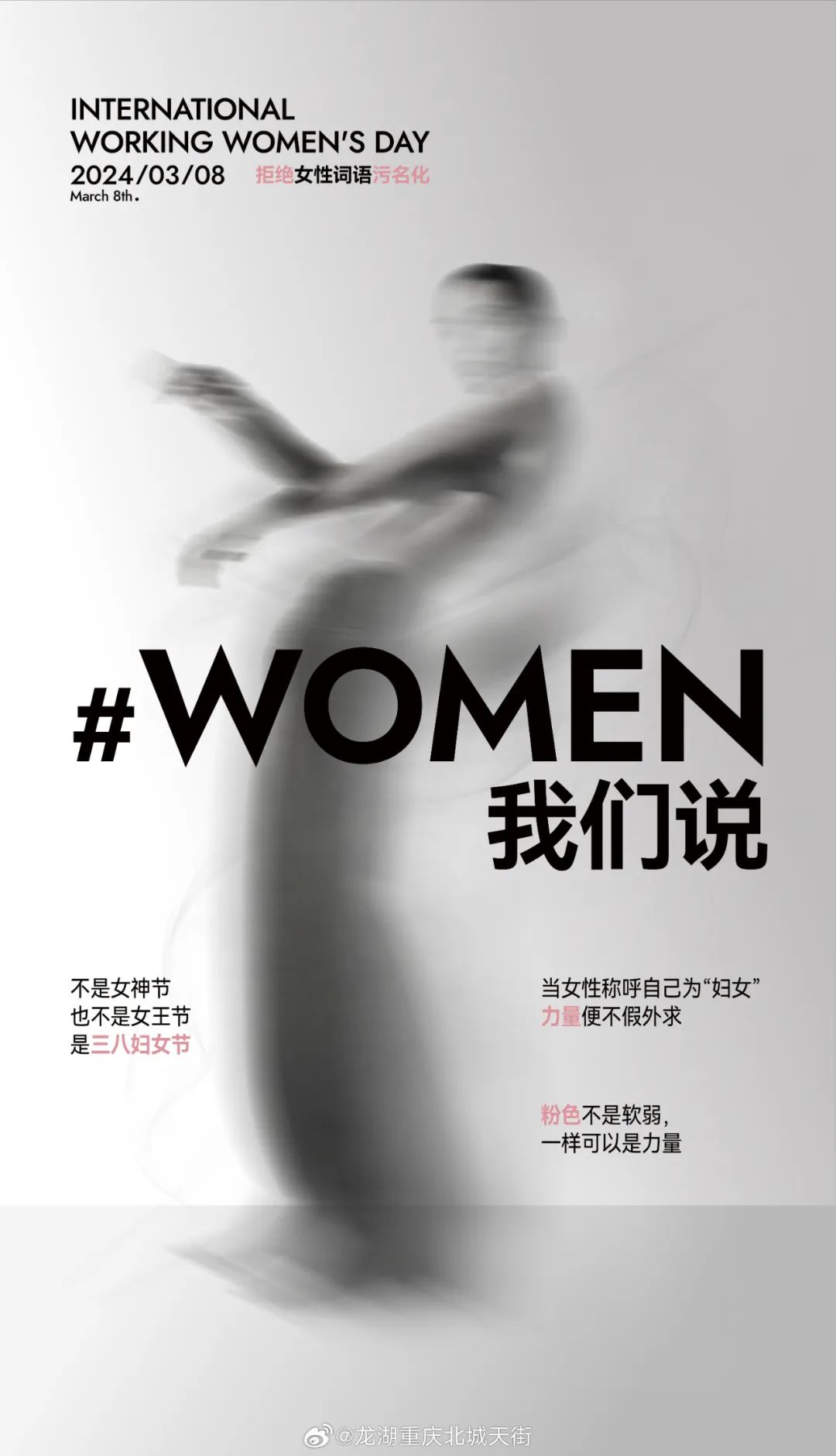
这种转变,也代表着女性从一种被定义,走向了一条自主定义的道路。
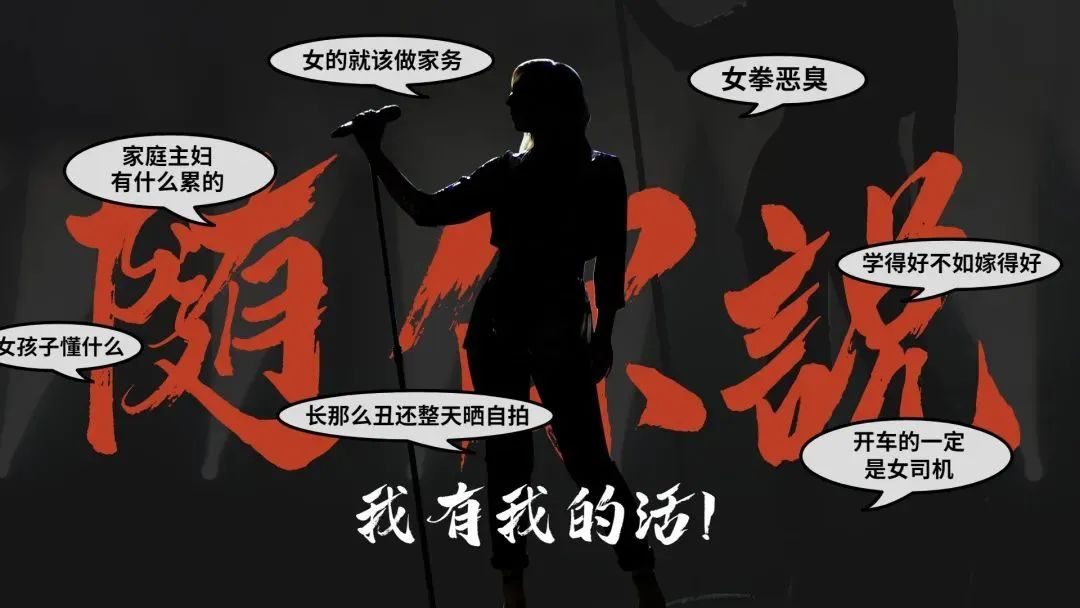
从字体你也可以看出来,以前都清一色的温柔,可爱,女性化,就像“芭比”一样。
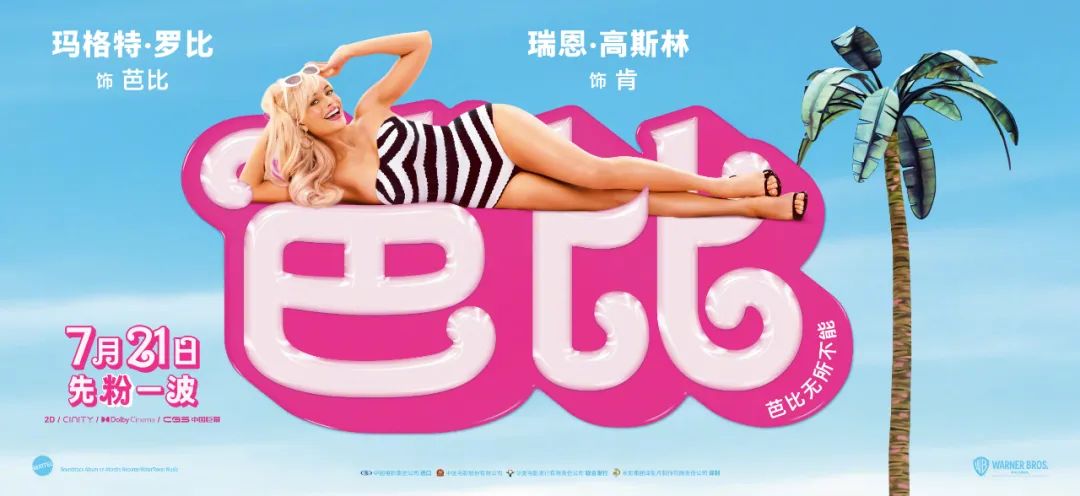
而当“芭比”的内在觉醒后,就有了更多面……
霸气的她
比如现在市场上最受欢迎的励志题材、大女主剧,都是打破了女性柔弱的固有印象,字形上也是偏霸气、恣意、潇洒的!
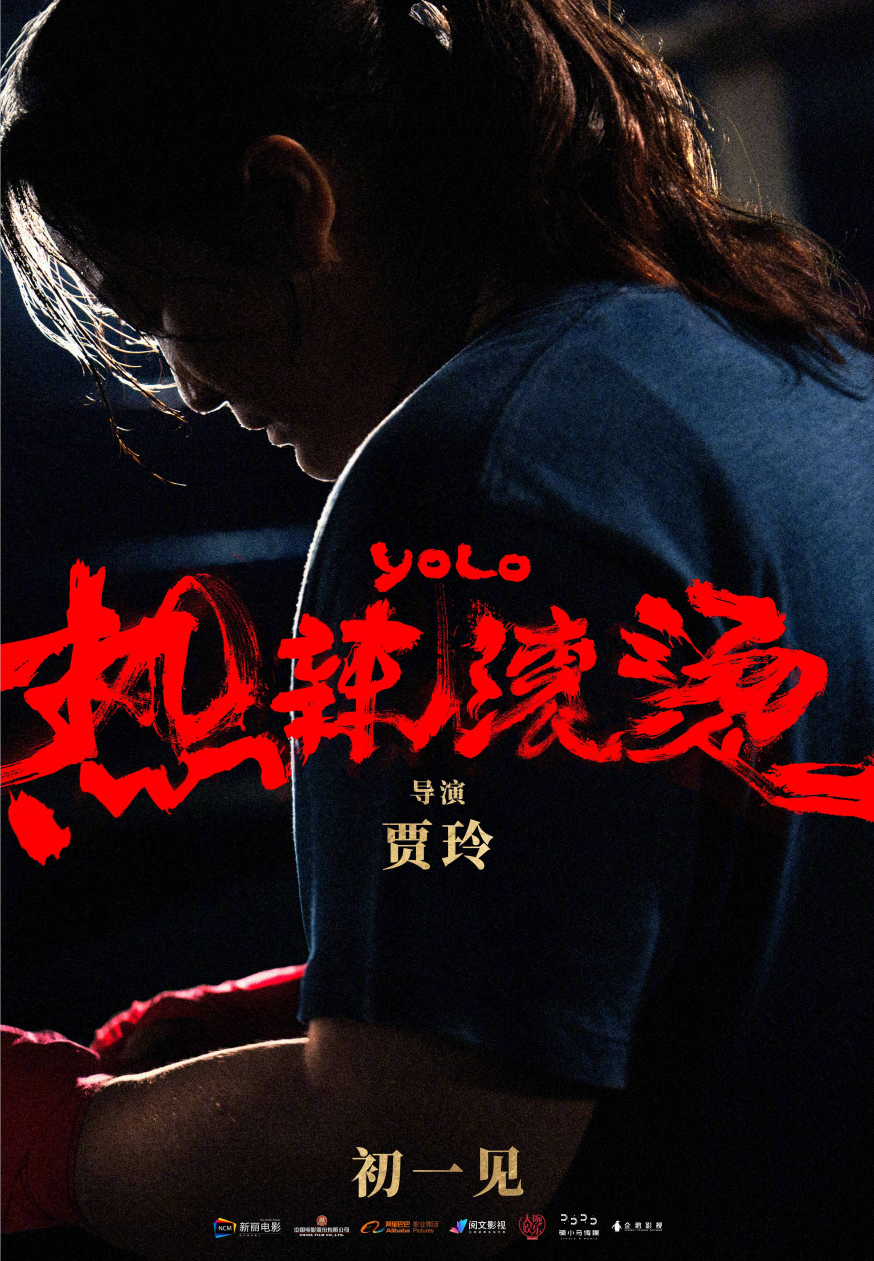
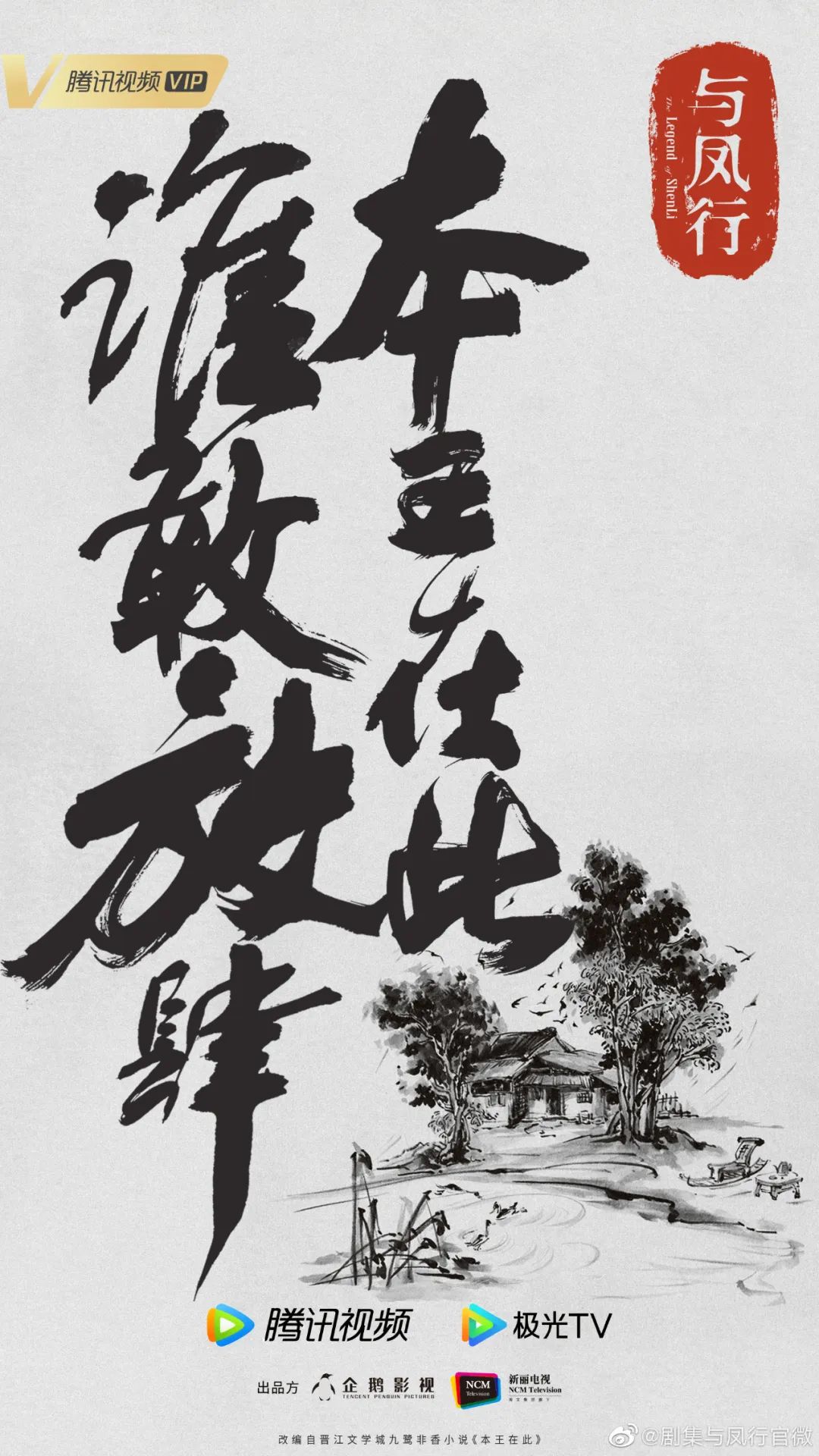
如果你想展现这一面,就要选择有内核的手写字。
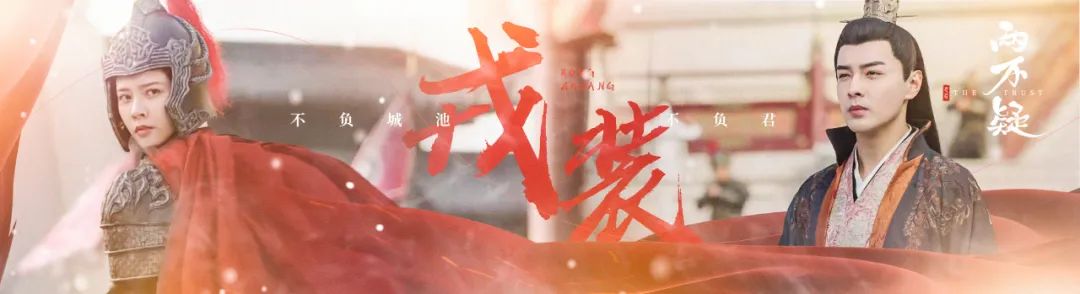
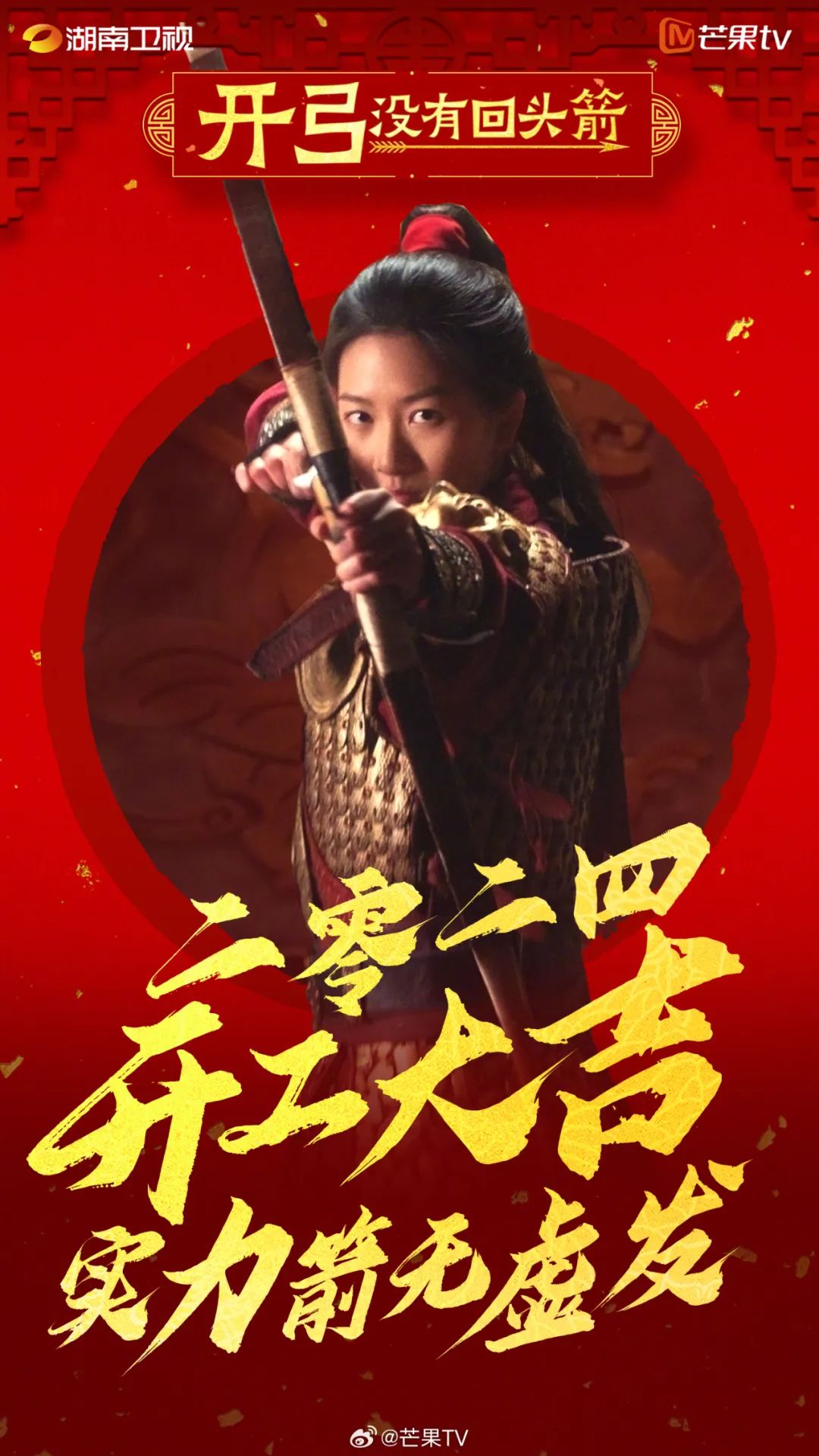
坚定的她
除了霸气外漏,内核的坚定,也能感受到满满的女子力!
未知的她
也不是说女性从此就要man化、女权化,这只是她反差较大的一面,她也可以展现如沐春风的一面。
青春活力的一面~
端庄典雅的一面~
幽默佛系的一面~
风韵复古的一面~
未来,还有很多面,等待发掘……
最后希望全天下的妇女,都能活成自己喜欢的样子。